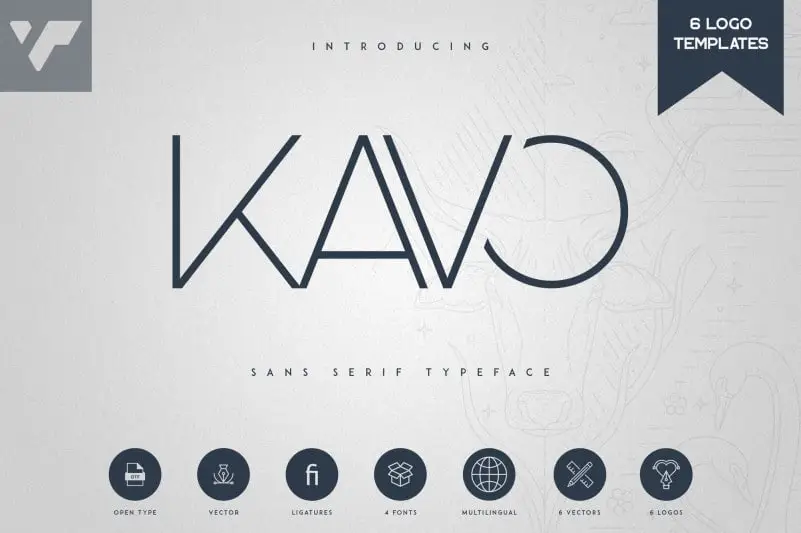
Kavo Sans Serif Typeface – 4 Weight + 6 Logo Templates – Download Grátis
Kavo Sans Serif Typeface é uma elegante tipografia séria que oferece 4 pesos de peso para aprimorar seu estilo. Este fonte moderno inclui ligaturas e suporta múltiplas línguas, tornando-o útil não apenas para textos normais, mas também para aplicação em logos. Junto com o Kavo Sans Serif Typeface vem um conjunto de 6 designs vectoriais incríveis que adicionam uma nova dimensão ao seu layout. Também acompanha 6 templates de logomarca prontas para uso, permitindo-lhe personalizar suas marcas de forma rápida e fácil sem ter que preocupar-se com a estrutura da fonte ou os formatos de imagem. Com Kavo Sans Serif Typeface, você tem uma ferramenta versátil que pode ser usada tanto em projetos profissionais quanto para trabalhos pessoais. Esse fonte traz estilo moderno e confiabilidade, sendo perfeito para qualquer aplicação onde a estética do texto é importante.